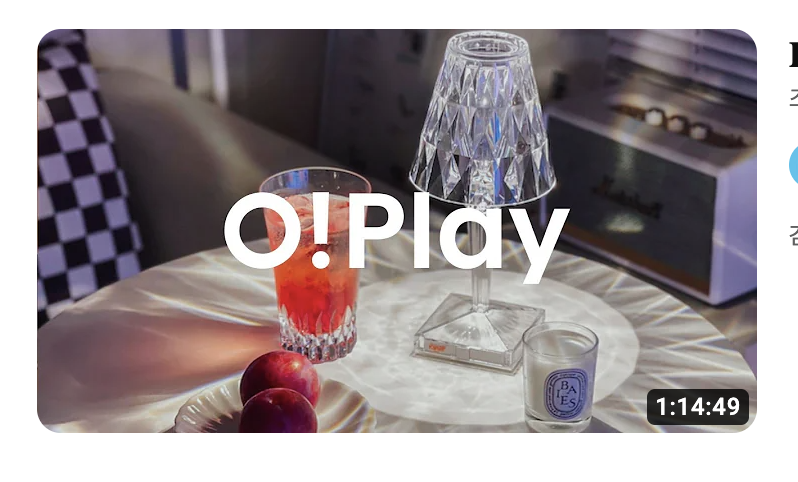
오늘의집 유튜브 오!플레이 폰트 궁금해요 elw*** 2023.04.21 https://www.youtube.com/watch?v=BR2qsRJAlBg 어떤 건지 아시는 분 계실까요..!!? 깔끔하고 가독성 좋네요 댓글 0 등록 쉽고 빠르게 가장 비슷한 폰트를 알고 싶다면? 이미지로 검색하기
어떤 건지 아시는 분 계실까요..!!?
깔끔하고 가독성 좋네요